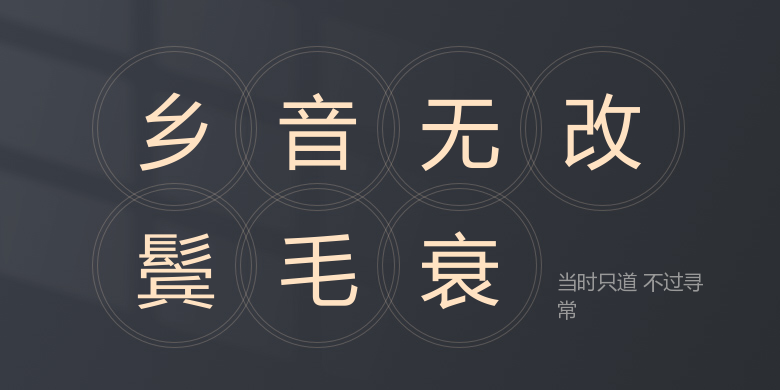
当时只道 不过寻常
当时只道 不过寻常,这款字体结构工整、笔画清晰,兼顾美观与易读性,适用于标题、正文、海报、包装、LOGO 等多种场景。字形优雅稳定,风格百搭耐看,适配日常排版与创意设计,让文字呈现更舒适、更具质感。当时只道 不过寻常一笔一画,皆是细节,以均衡的比例、流畅的线条打造舒适视觉体验,字形端正大气,风格简约现代。无论是商业设计、品牌宣传还是日常排版,都能轻松驾驭,让文字更有格调与力量。当时只道 不过寻常字体下载。